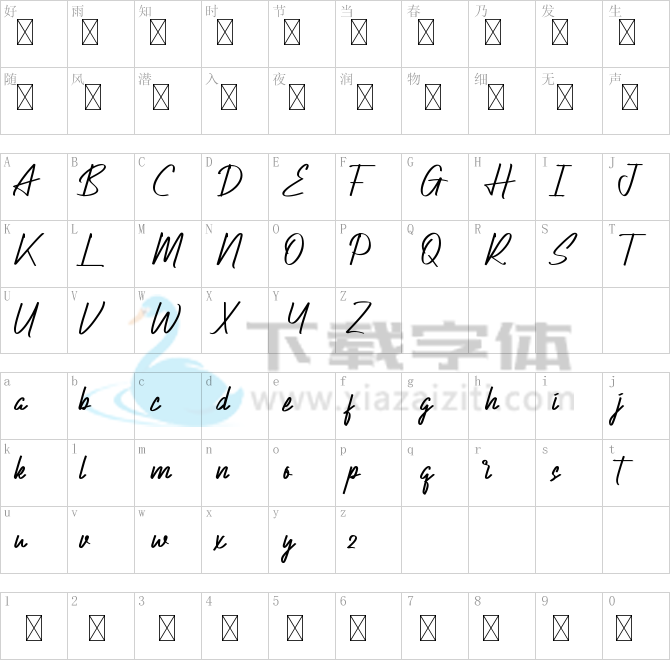
Actinide Demo.ttf字体下载,这款字体结构工整、笔画清晰,兼顾美观与易读性,适用于标题、正文、海报、包装、LOGO 等多种场景。字形优雅稳定,风格百搭耐看,适配日常排版与创意设计,让文字呈现更舒适、更具质感。Actinide Demo.ttf字体下载一笔一画,皆是细节,以均衡的比例、流畅的线条打造舒适视觉体验,字形端正大气,风格简约现代。无论是商业设计、品牌宣传还是日常排版,都能轻松驾驭,让文字更有格调与力量。Actinide Demo.ttf字体下载字体下载。